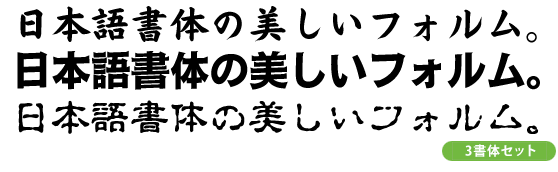
「伝わる和テイストの書体」タイトル・装飾向け3書体パック
SMotoyaOkaiLiteN-W5,MotoyaTohitsuLiteN-W6,MotoyaKoinLiteN-W5
「落ち着いた雰囲気にしたい」「和の空気感を出したい」――そんな時にぴったりの3書体をセットにしました。
Sモトヤ大楷、モトヤ刀筆、モトヤ古印体は、それぞれ異なる個性を持ちながらも、共通して“日本らしい情緒”や“あたたかみ”を感じさせる書体です。
和食店や旅館、観光イベントのチラシ、商品パッケージ、年賀状、同人誌のタイトルなど、和テイストを必要とするあらゆる場面に自然に馴染み、雰囲気づくりをサポートします。どれも太めで視認性が高く、印象づけたいタイトルや見出しに最適。派手すぎず、品よく“伝わる”和の表現が可能です。